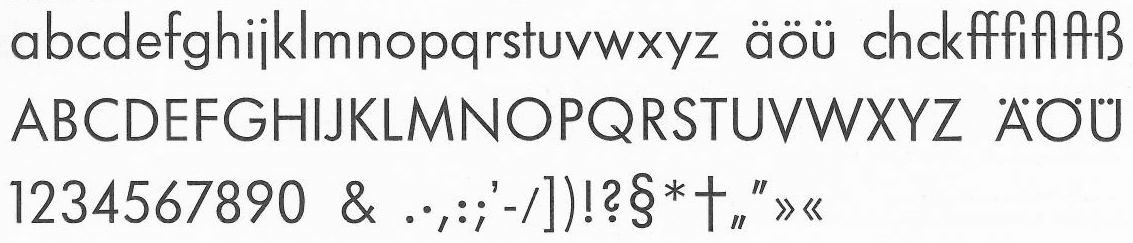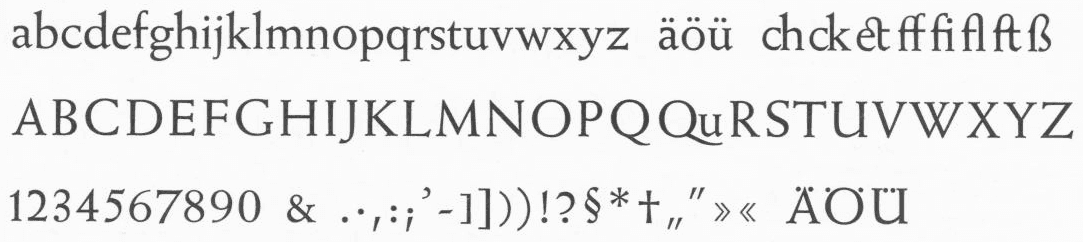
Bezeichnung „Obeliskus“ oder „Obelisk“ für das Zeichen „†“
Wenn sich nur die Fraktur da wieder mal ein eigenes Süppchen kocht und solch ein Spezialfall dann nicht in Unicode berücksichtigt wird, na ja …
Nun, auch für solche Sondergebiete gibt es in Unicode ja eine konforme Lösung, über die Privat Use Area, für den es dann eben für solche nationalen Sondergebiete durchaus auch wieder eine Normung gibt, an die man sich als Schriftgestalter halten kann, und an die sich auch viele Font-Herausgeber halten, ich denke hier an MUFI, SIL und UNZ1
Über ein Beispiel haben wir ja schon gesprochen: das Auslassungszeichen hat keine eigene Codestelle. Ein weiteres Beispiel: Der Doppelpunkt, laut Wikipädie in den meisten Ländern außer den englischsprachigen das bevorzugte Zeichen für die Teilung, wird bei den Engländern und Amerikanern in der Mathematik wohl nur als Zeichen für Verhältnisse benutzt. Entsprechend ist im Unicode nur ein mathematischer Doppelpunkt mit dem Namen „Ratio“ als Verhältniszeichen enthalten (U+2236), als Teilungszeichen ist er nicht vorgesehen. In der Lucida Sans Unicode besteht dieses Zeichen aus drei, nicht zwei übereinanderstehenden Punkten — ich weiß nicht, ob das eine erlaubte Form des Verhältniszeichens ist oder ein Fehler in der Schrift.
Wie angekündigt liefere ich hier noch zwei Beispiele für verschiedene Formen von Auslassungs- und Anführungszeichen bei Lateinschriften. In beiden Beispielen sind wieder ein gekrümmtes Auslassungszeichen und gerade Anführungszeichen zu sehen. Anklicken zum Vergrößern.
Futura-Buchschrift
Weiß-Antiqua